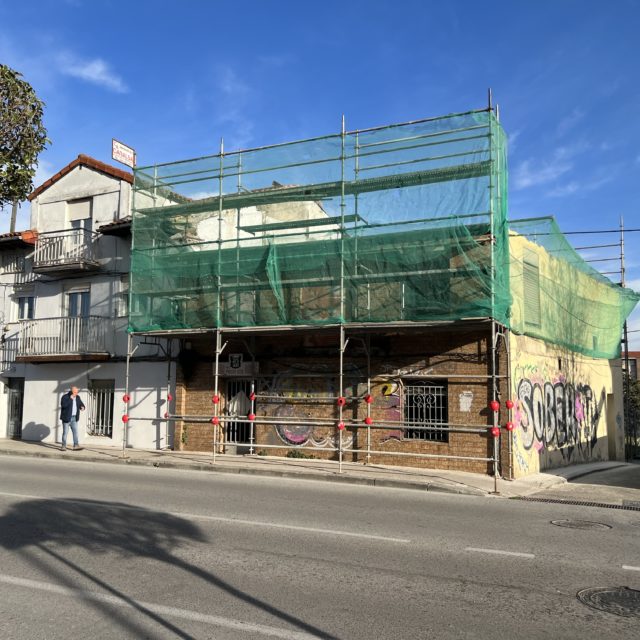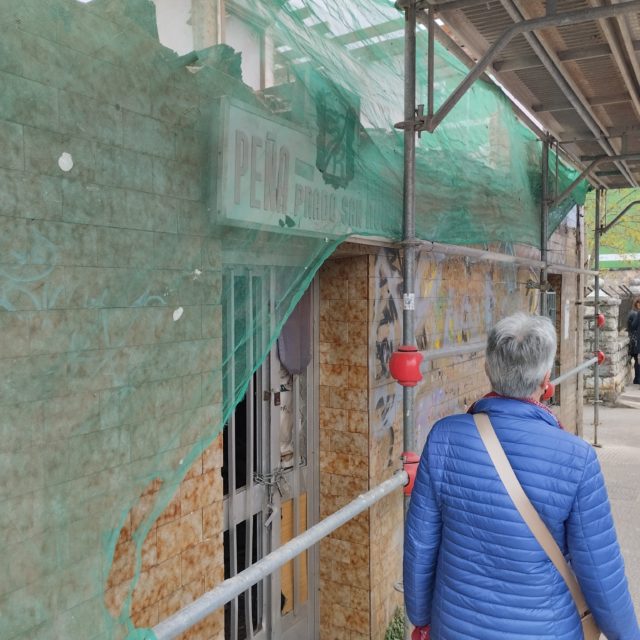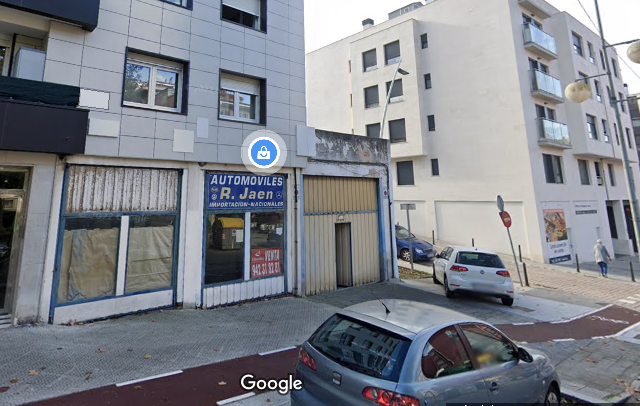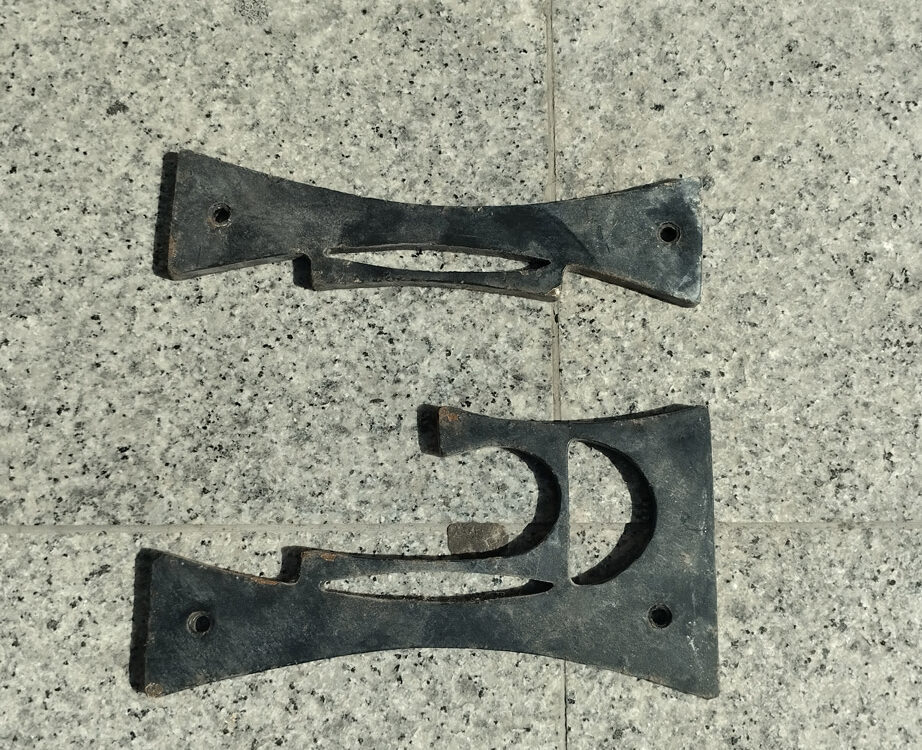
Peña San Roque y Automóviles R. Jaen
La semana pasada, tras varios avisos de custodios de que estaban demoliendo el edificio y visitas a la obra, pudimos rescatar el rótulo de la “Peña San Roque”. El Patrimonio Gráfico también es aquello que hace barrio, y este era uno de esos carteles que estaba en General Dávila desde hace más de 40 años. Ahora queda preservado dentro del archivo del proyecto.
Por otro lado, también el mismo día, pudimos recoger el cartel de “Automóviles R. Jaen”, por el comienzo de las obras de reforma del local, en la calle Tetuán. El negocio de importación de vehículos tenía cerca de veinte años.